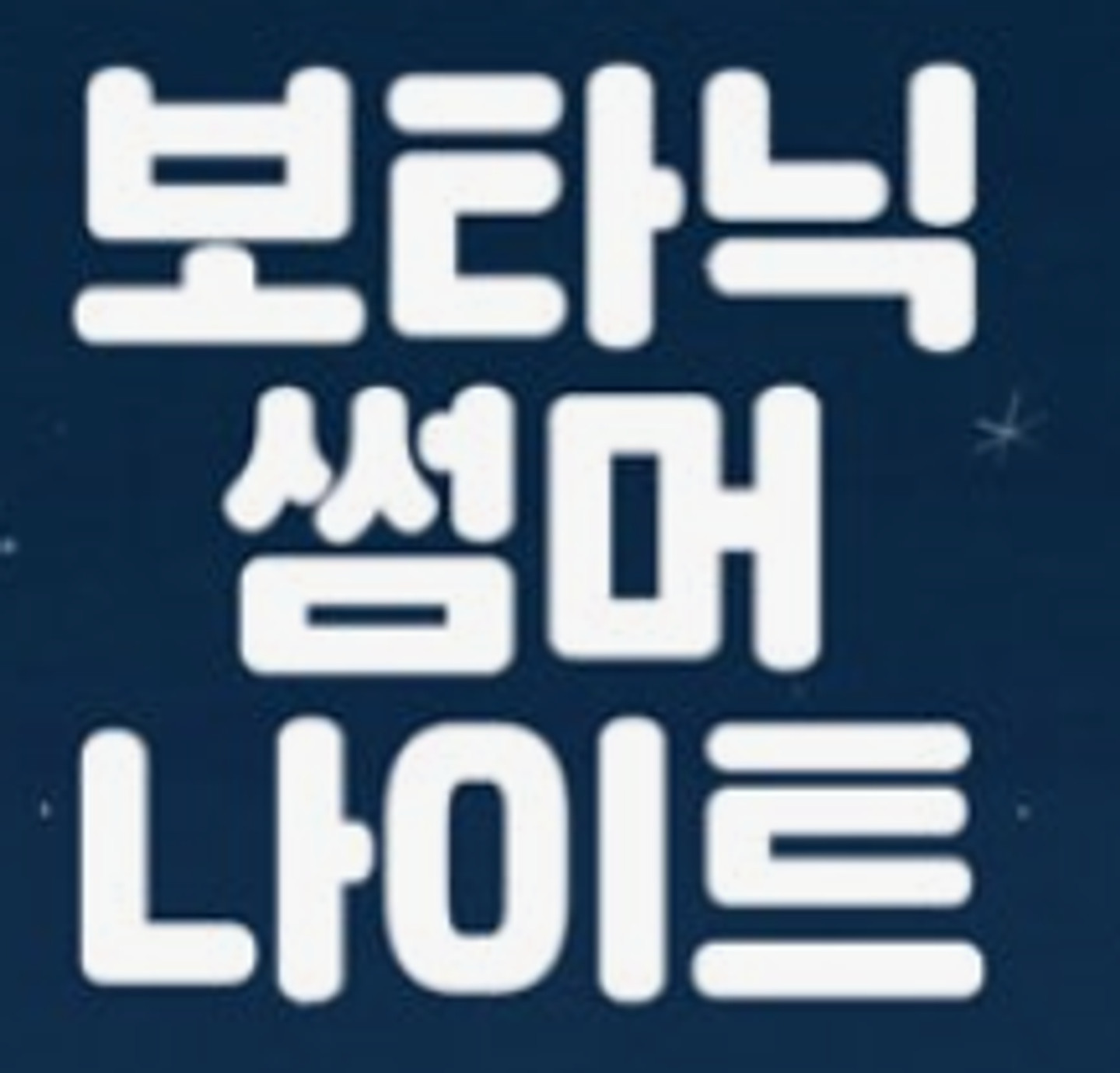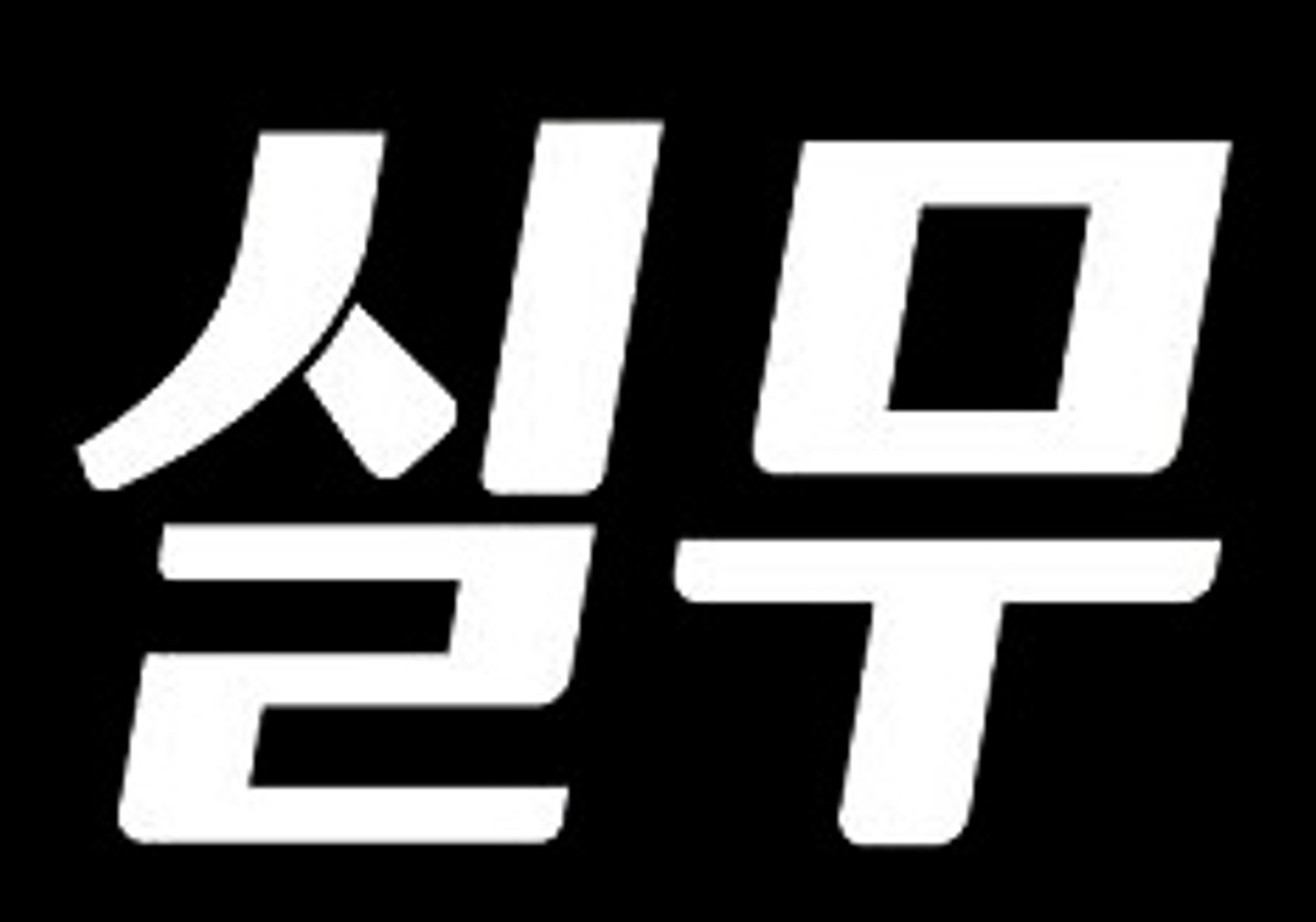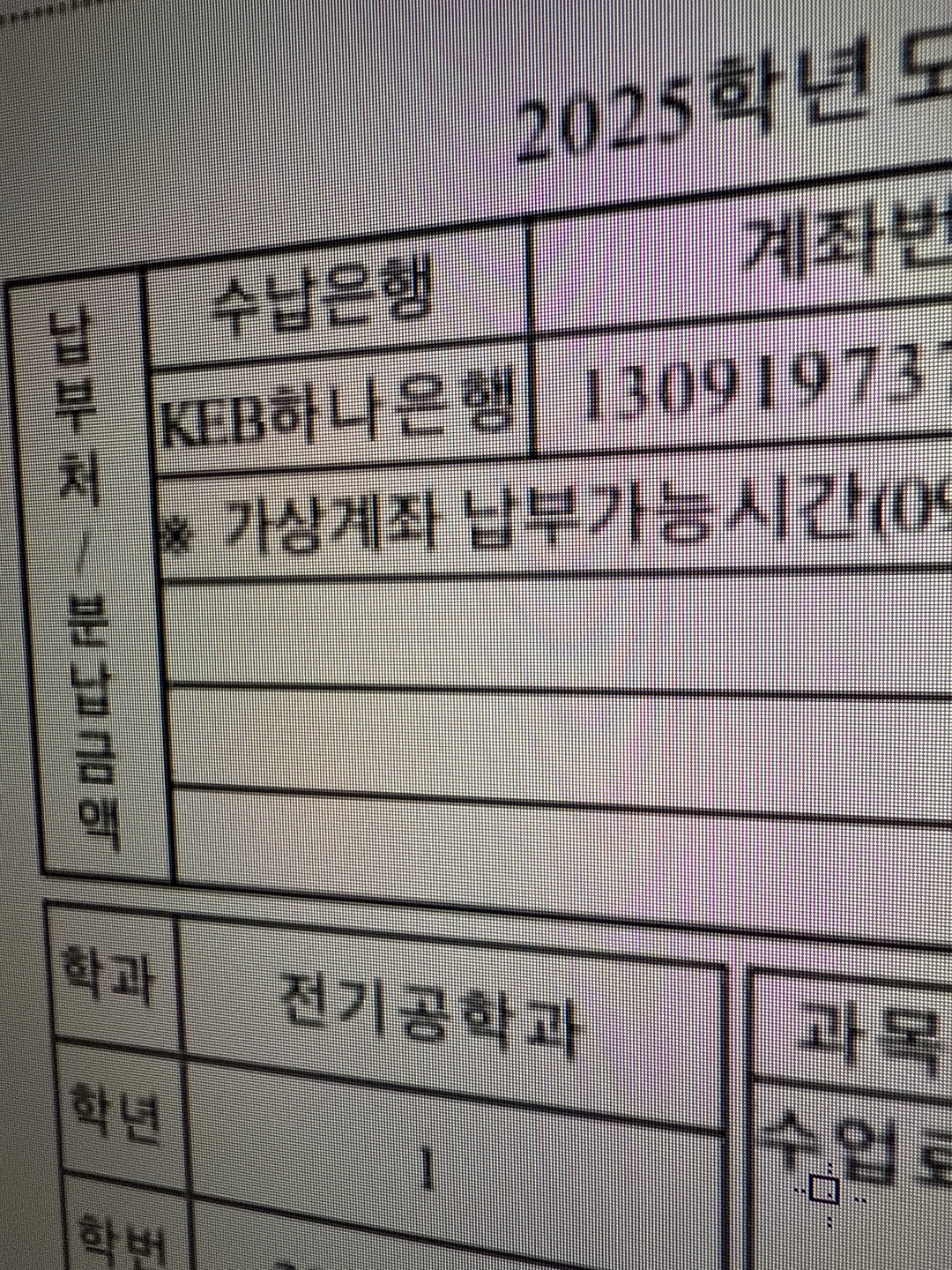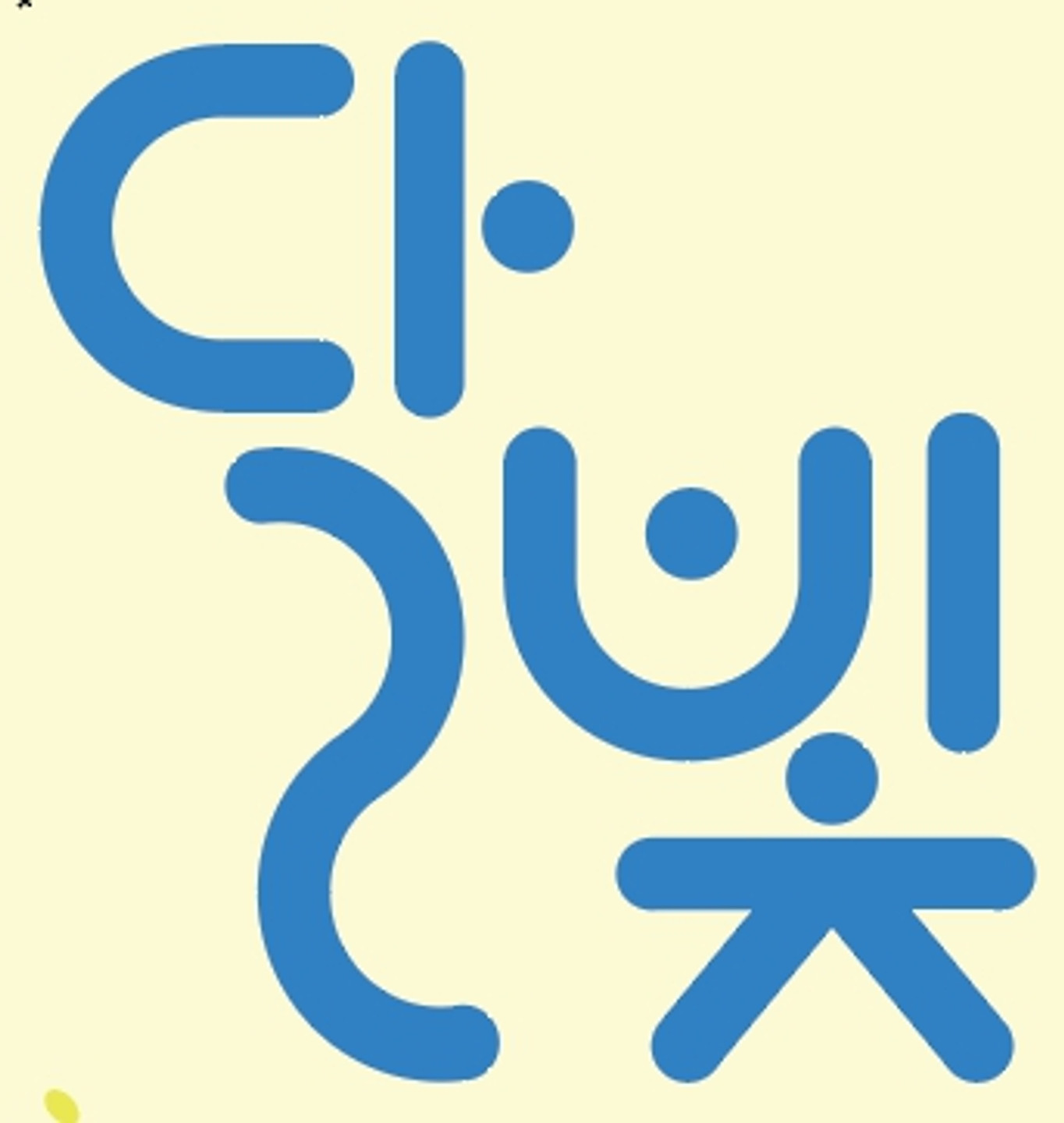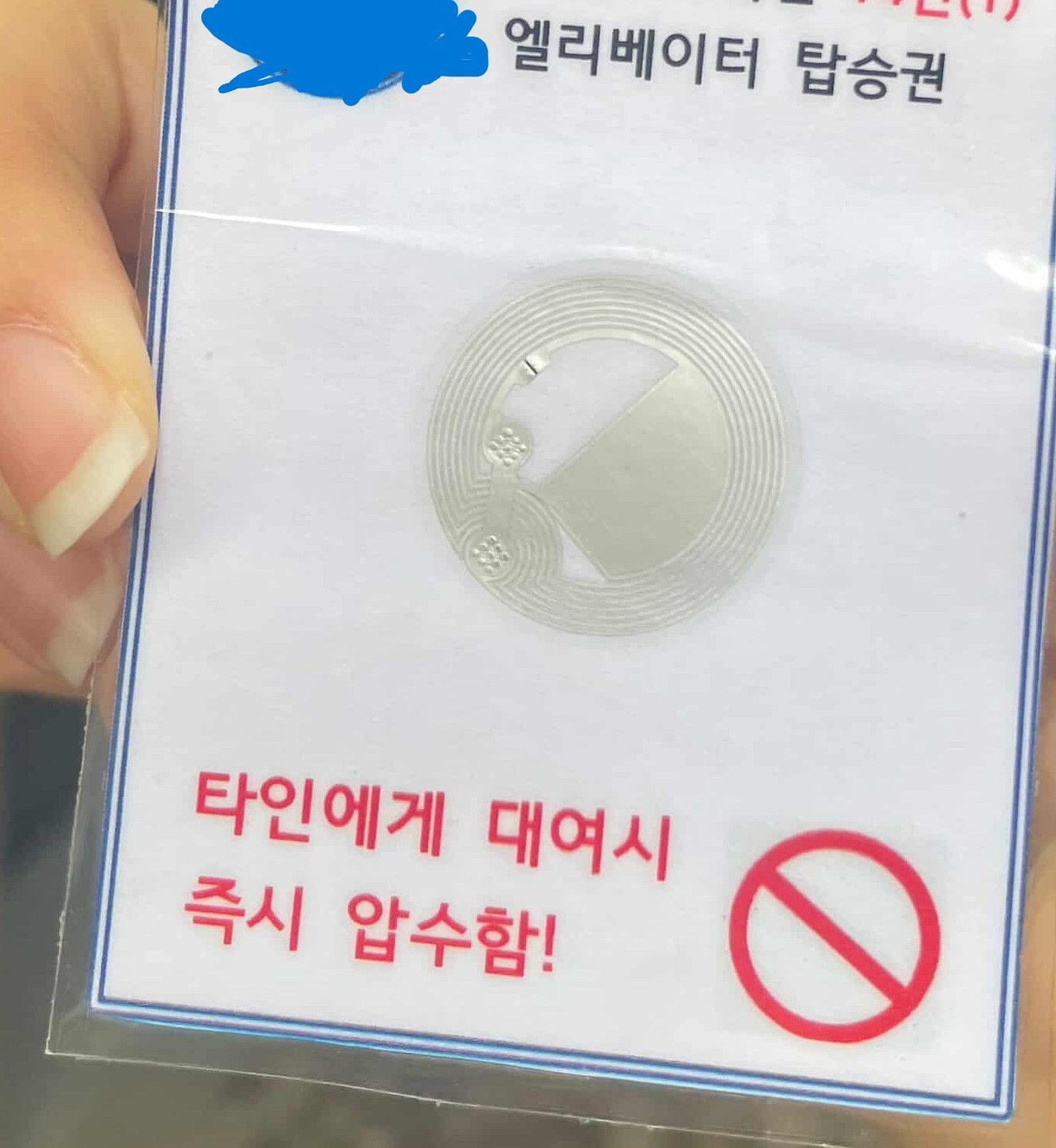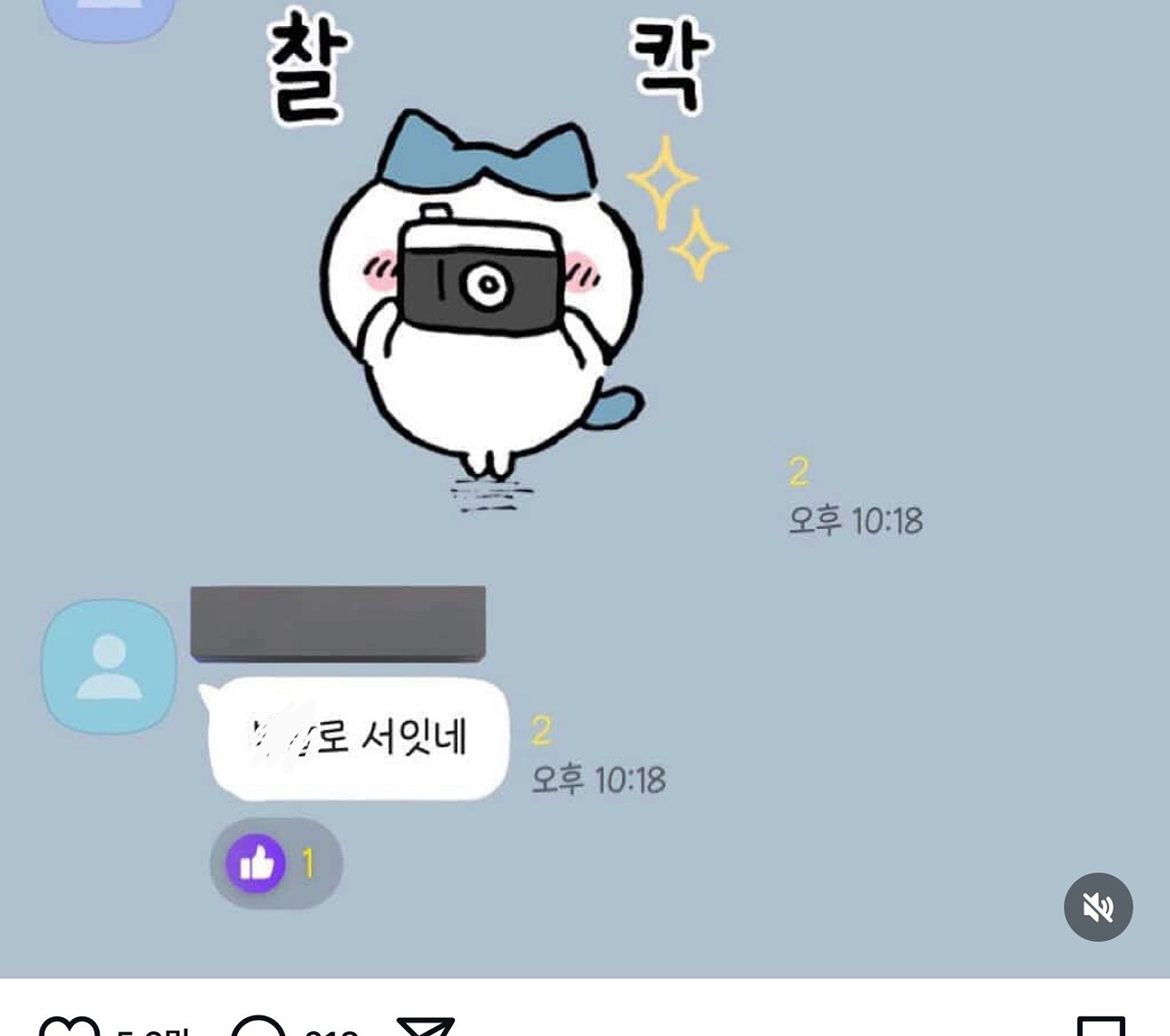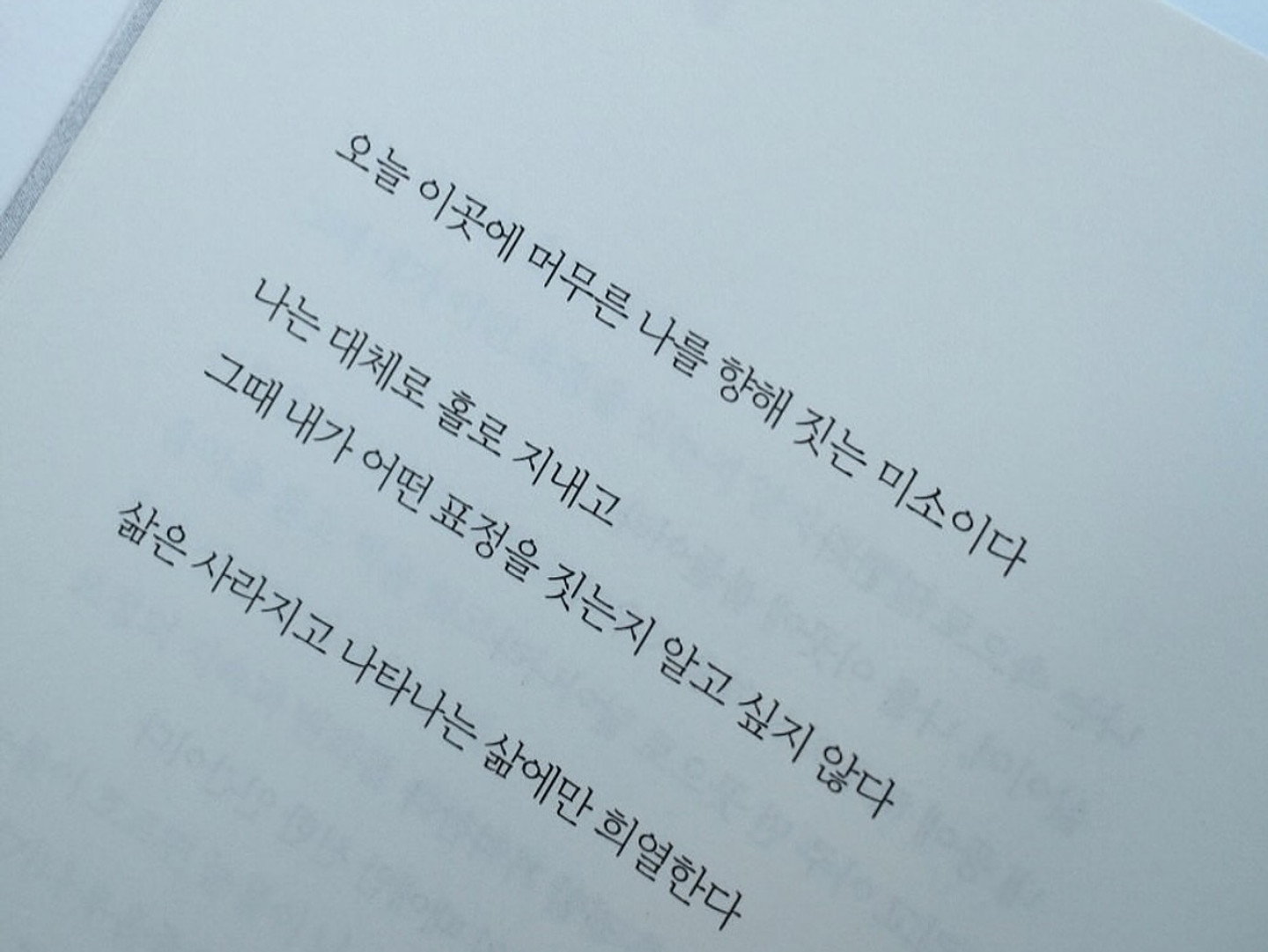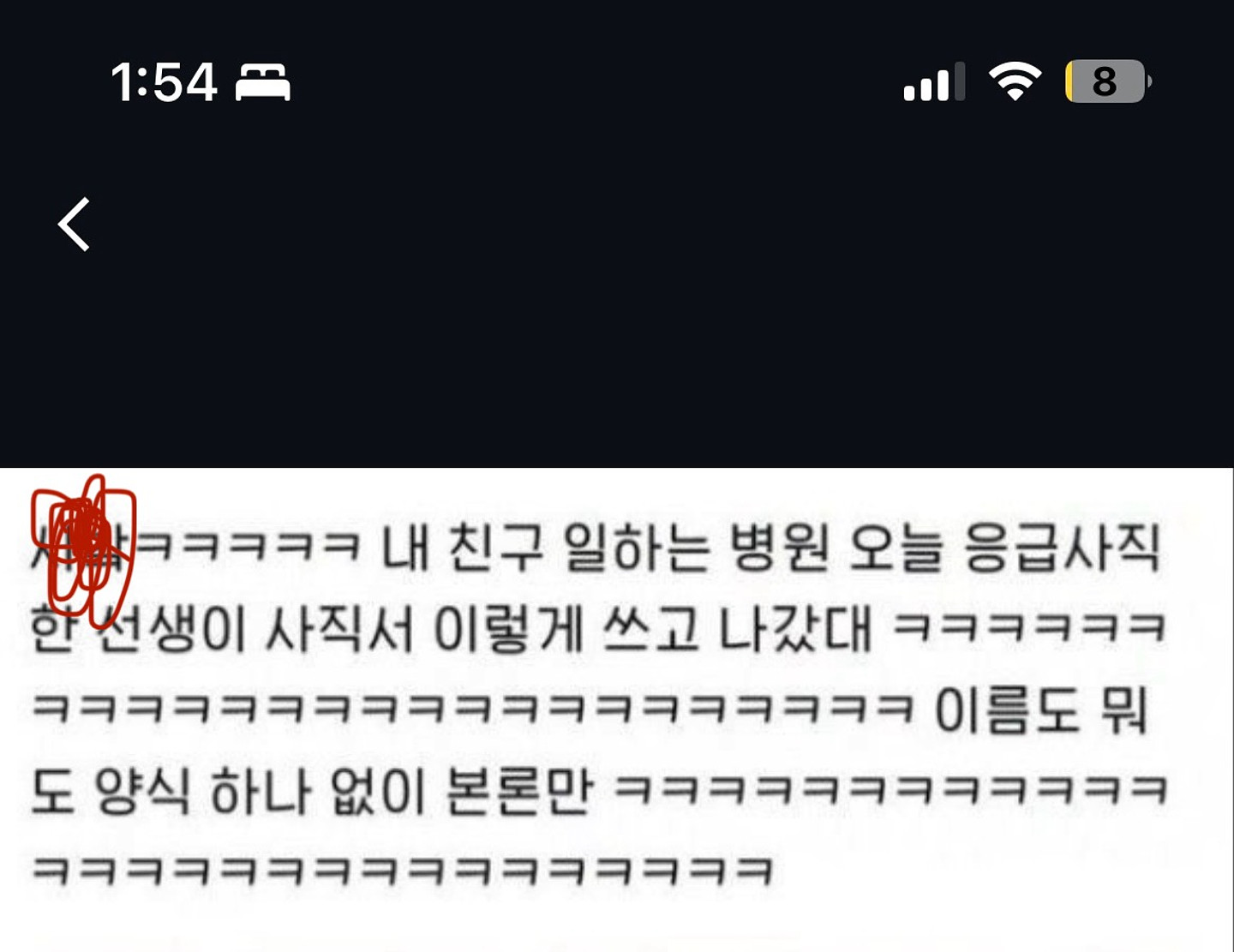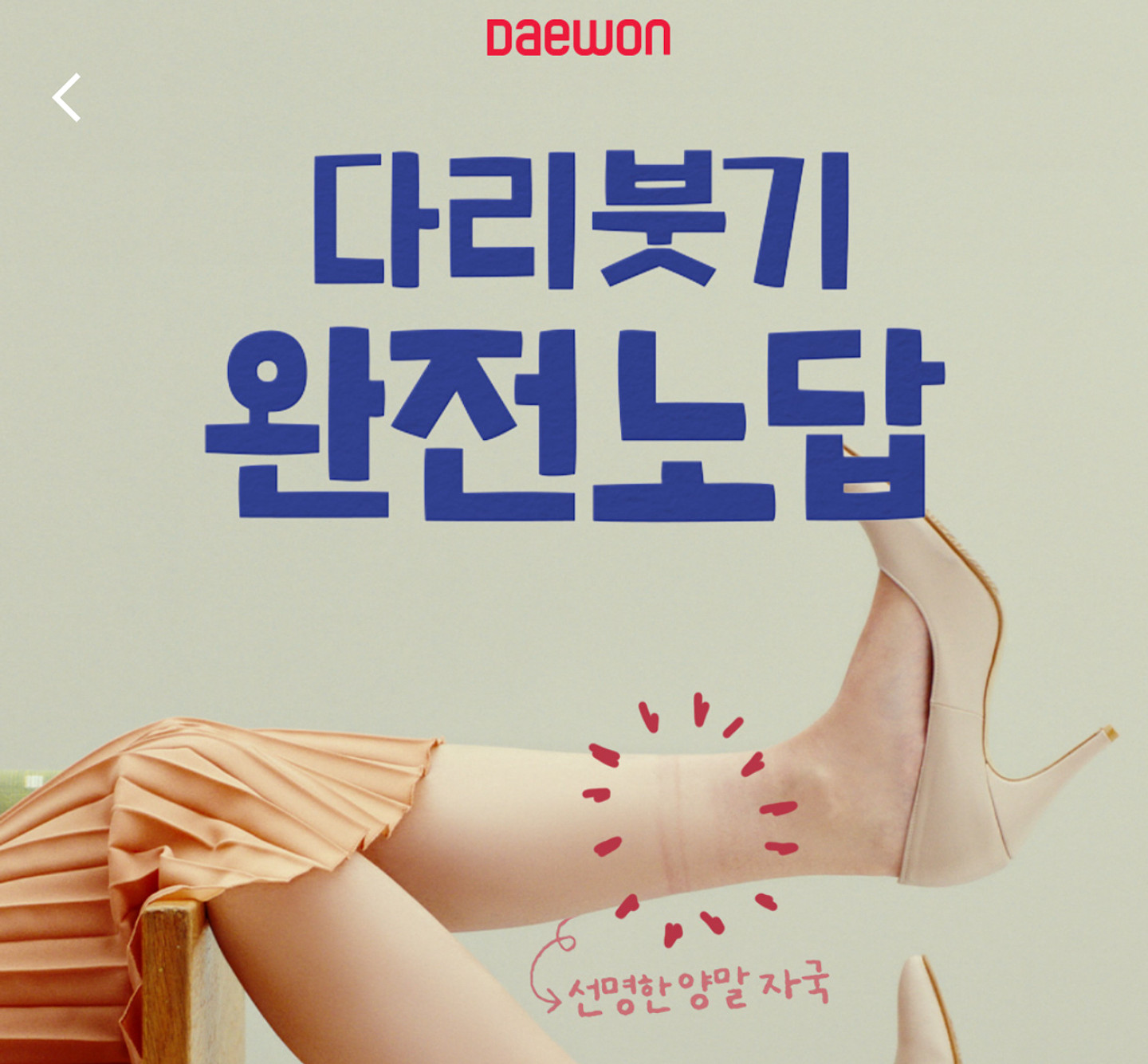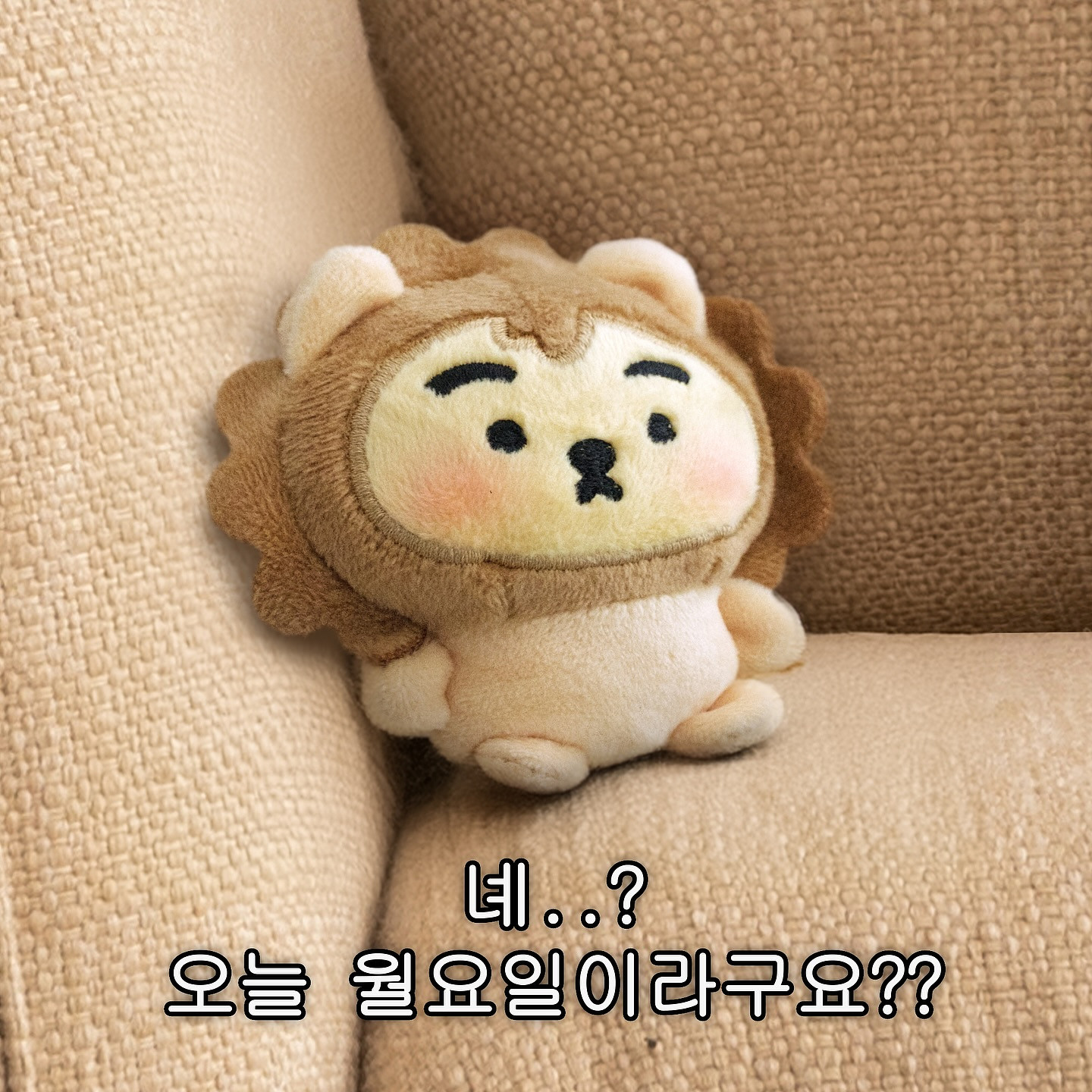
여기 사용된 폰트 다 뭔가요?
헤이세이노트손글씨라고 써져있는데, 검색해도 나오질 않아서요. 무슨 폰트일까요? 제일 비슷한 일본어 폰트라도 알고 싶습니다.
이 폰트 뭘까?
이건 무슨 폰트인가요?
이게 무슨 폰트 인가요?
뭘까용
이 폰트 뭘까요 ?
무슨 폰트일까요. 답변 감사드립니다
GPT로 만든 폰트인데 최대한 비슷한 폰트 있으면 추천부탁합니다
이 폰트 뭔지 아시는 분... ㅠ!!
혹시 줄리엔강 로고 폰트 뭔지 아시는 분...!
이거 서체 알 수 있을까요? 제가 보기엔 켈리같긴한데 아니면 비슷한 서체라도 있을까요
이 숫자 무슨 폰트인가요?
무슨 폰트일까요???
무슨 폰트인지 알려주세요
연두색 글씨 무슨 폰트인가요?
이 폰트 뭔지 아시는분 계실까요?
어떤 폰트인지 알고싶습니다
일드 번역 자막인데 뭔지 아시는분
김된모님 영상 폰트인데 뭔지 알 수 있을까요??
삼성 갤럭시 폰트 궁금해요! 유럽 여행 후 소매치기 당해서 옛날 핸드폰의 모든 걸 찾고 있습니다… ㅠㅠ
유튜브 보던 중 자막 폰트가 궁금해져서 여쭤봅니다
혹시 m&m 로고 폰트도 아실까요? 감사합니다!!
안녕하세요. 폰트 아시는 분 계실까요? 미리 감사드립니다
늘 감사한 눈누 전문가분들 이 폰트 혹시 아시는 분 계실까요?
안녕하세요. 도움부탁드릴게요. 이 폰트 너무 궁금해요
이 폰트 뭘까요 ?!
이거 무슨 폰트 일까요?ㅠㅜ
무슨 글씨체인지 알수있을까요?
이 폰트 어떤 폰트인지 알려주세여,,
이런 스타일의 무료 폰트 있을까요?
혹시 슬리피 썸네일로 쓰이는 폰트 알려주세요ㅠㅠ!!
두개 다 알려주실수잇을까요ㅜㅜ
숫자 폰트 알수 있을까요?
자음 획의 두께가 다른 점, 시옷의 모양, 이응과 히읗을 제외하면 전부 각진 자음, 기역과 키읔의 세로길이가 모음과 같은 점
저 커다란 글씨 폰트가 뭘까요?
명랑극장이랑 비슷한데 삐침이 달라요 ㅠ ㅠ 찾아주세요!
이 폰트 뭘까요?...
뭔서체일까용?? 조합한걸까용
눈누에서 받은 폰트인데 갑자기 깨지면서 뭔지 찾을 수가 없음
16x16 lcd 폰트
카카오톡 쇼핑 화면 > 더위극복특가 이벤트화면에 나오는 카테고리 타이틀입니다. (볼드체)
이 폰트 좀 찾아주세요 ㅠ
이 폰트 뭔가요??
이 폰트가 뭔지 궁금합니다
이 폰트 이름 뭐에요?